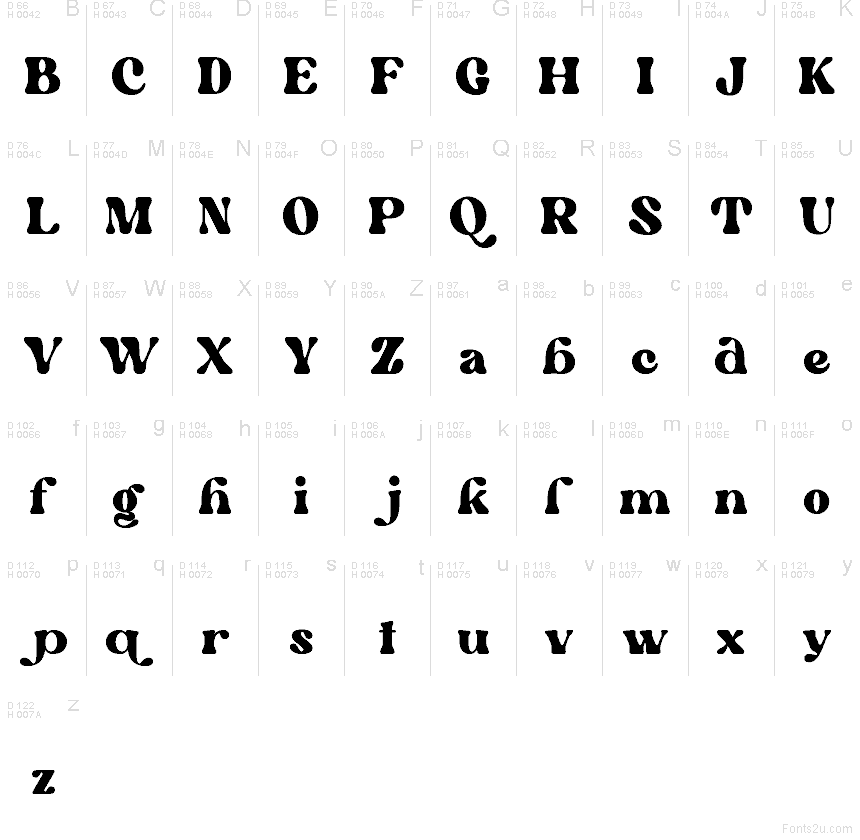
Peach Melon, de Taboja Studio, es una tipografía display de estilo retro y groovy, inspirada en el espíritu suave y exuberante del lettering de los años 70. Sus formas anchas y sólidas se expanden en curvas redondeadas, mientras que los detalles en espiral y los juegos de grosor le dan a las letras una riqueza orgánica, casi frutal, como si estuvieran dibujadas a mano.
Esta fuente gratuita es ideal para pósteres musicales, portadas de álbumes, diseño de empaques, identidad de cafeterías y titulares editoriales con un toque nostálgico. Funciona especialmente bien en titulares cortos y tarjetas de título, donde sus formas generosas y curvas dramáticas tienen espacio para dar carácter a la composición.